/CURLY FONTS/
> Mấy font này mình khuyên các bạn nên áp dụng vào edit graphic,horror style thì sẽ được hơn <
1/Wizards Magic
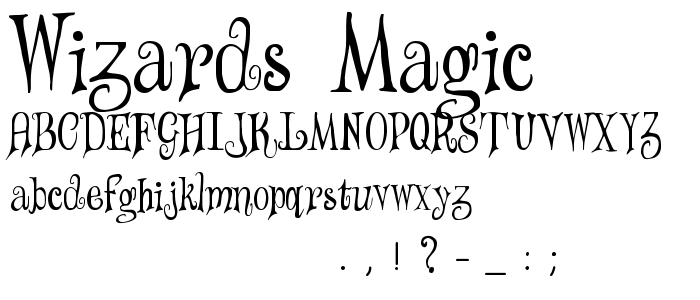
2/DK Jambo
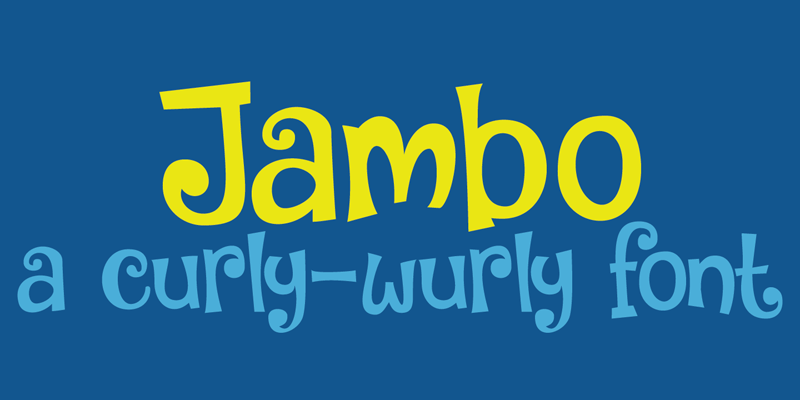
3/ Metshige
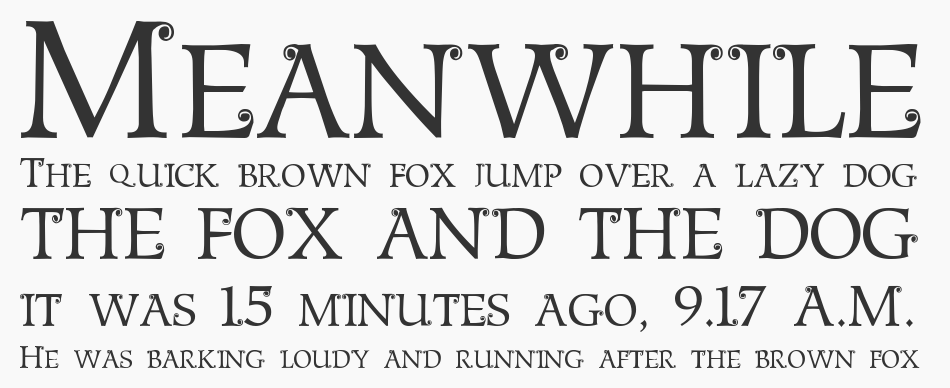
4/Unchanged Thoughts
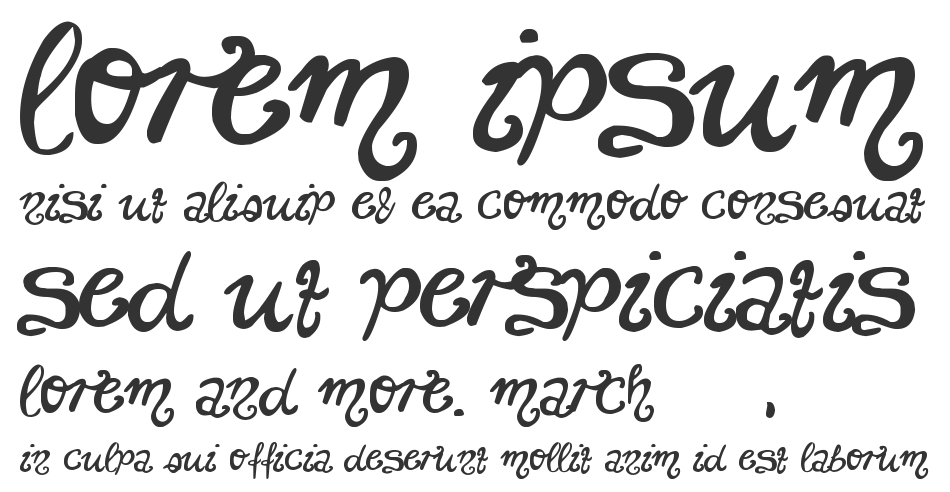
5/ Alpengeist
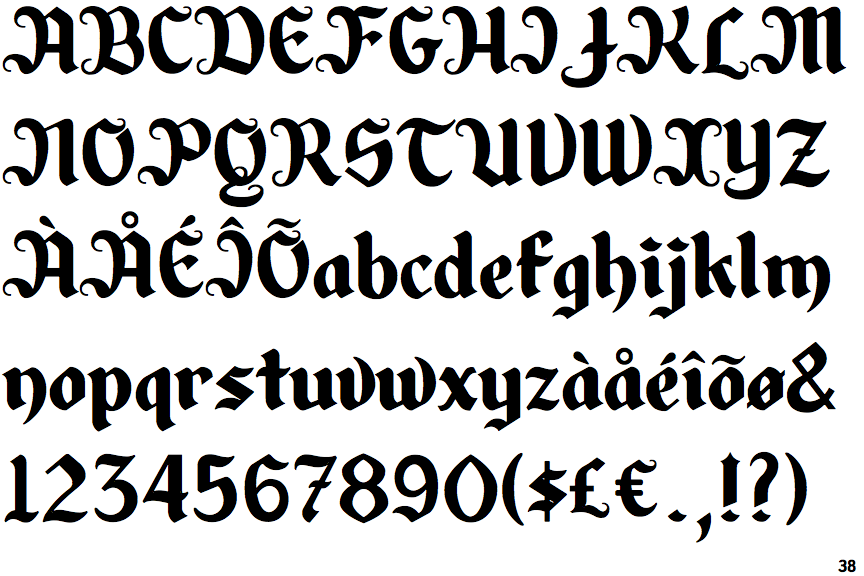
6/ Baileywick Curly
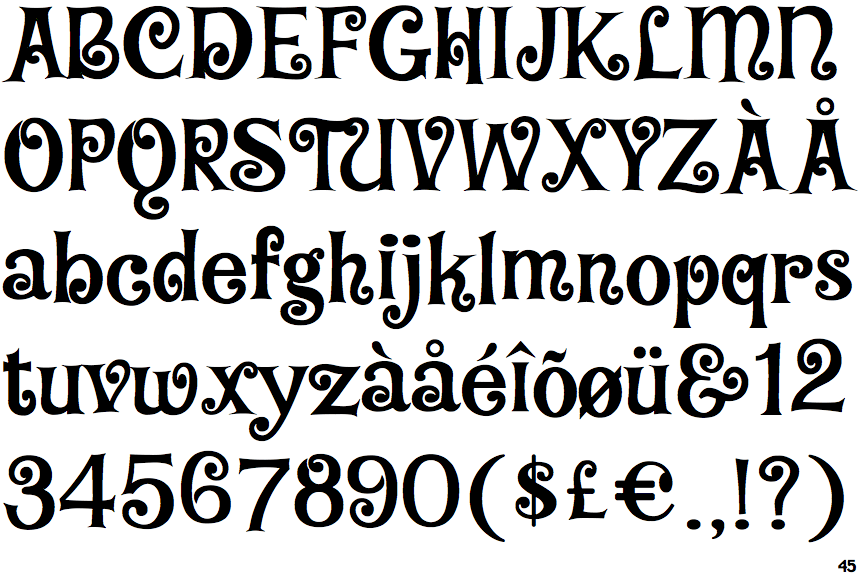
7/ The Gingerbread House
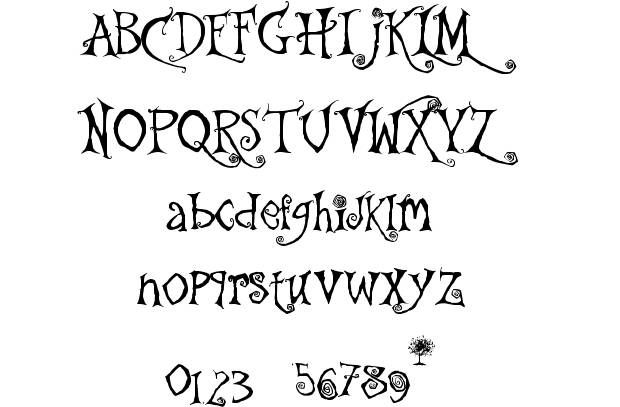
8/Janda Curlygirl
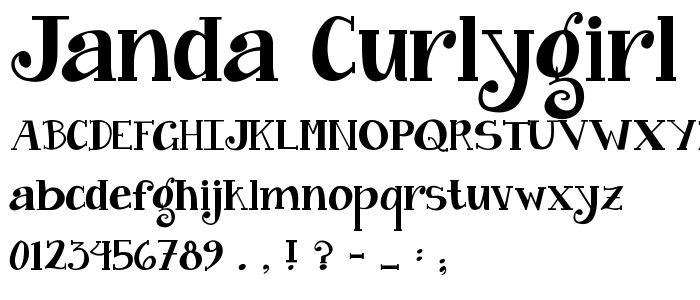
9/ Agreloy
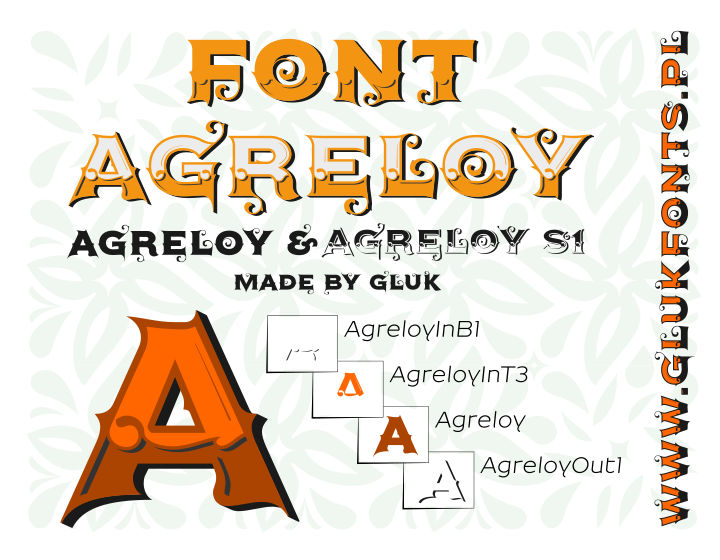
10/ Funky Mother
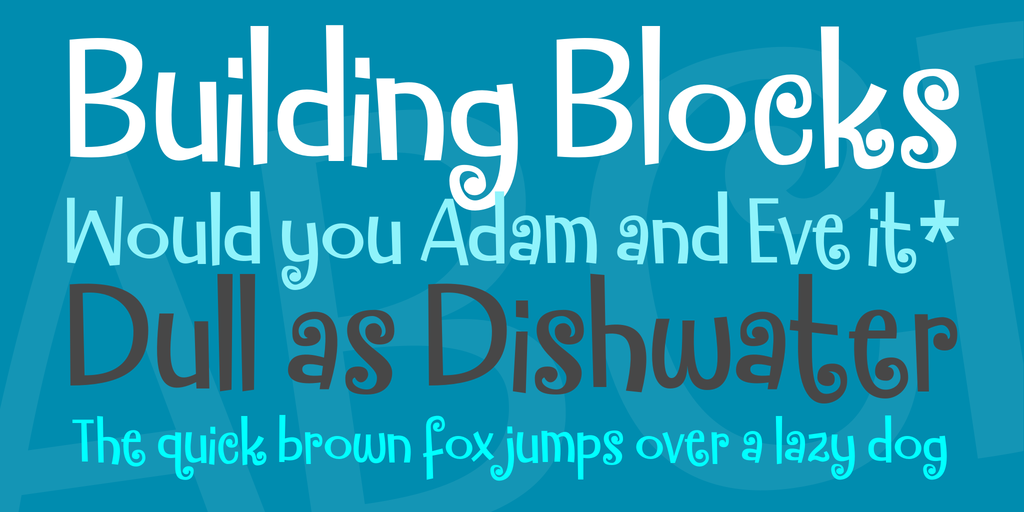
11/Curly Stars
12/ Musicals
* BONUS :V
> Curly ( VH ) Chắc font này ai cũng có nhưng thôi share cho mấy bạn yêu thể loại romance,hiện đại : D